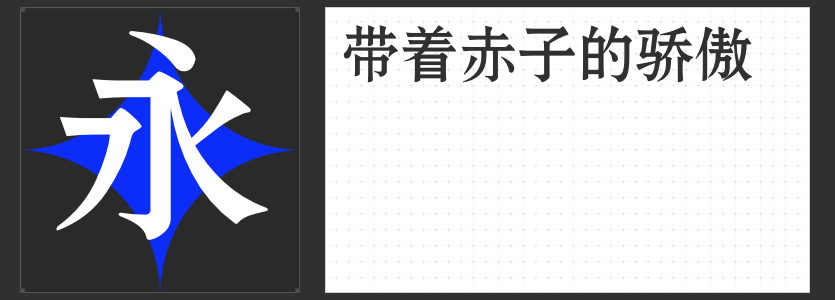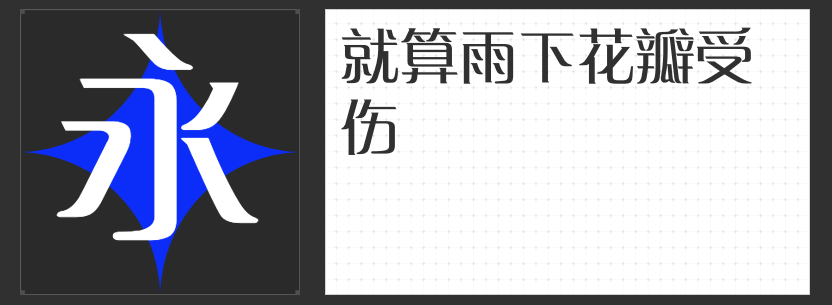
广告就是要端庄大气!四款字体推荐
在广告设计中,字体选择至关重要,它不仅能够传达信息,还能强化品牌形象,激发观众情感。今天,为大家推荐四款来自励字字库的精选字体,它们各具特色,非常适合用于广告设计中,为你的创意增添无限可能。
第一款推荐的是励字超级勇士简 中粗。这款字体以其严谨庄重的字型设计脱颖而出,笔画以直线为主,弧线简洁明了,展现出一种力量与美感并存的视觉效果。起笔与收笔采用斜切手法,与转折处的圆弧处理相得益彰,使得整体字体流畅而舒适,非常适合用于需要强调力量感和专业度的广告中。
接下来是励字励倩简。这款字体基于扁平硬笔的书写轨迹设计,笔锋柔和,避免了尖锐感,以微小的圆弧呈现,给人一种温婉而舒畅的感觉。字型方正饱满,笔划粗细对比适中,既婉转妩媚又不失温顺乖巧,适用于营造温馨、亲切的广告氛围。
励字宋黑简则是一款融合了黑体与宋体特点的字体。它保持了黑体的端正大方,横竖笔画挺拔有力,同时融入了宋体的典雅与工整。字体清秀,横轻竖重,结构均匀,笔法严谨,既美观又实用,非常适合用于需要展现品牌专业形象与高端品质的广告设计中。
最后推荐的是励字粗圆简繁。这款圆体字体字形端正严谨,笔画四周圆润,给人一种和谐而亲切的感觉。在广告设计中使用这款字体,能够营造出一种温馨、友好的氛围,特别适合于儿童产品、家居用品等温馨主题的广告宣传。
这四款励字字库字体各具特色,能够满足不同广告场景的需求。无论是强调力量感、温馨亲切还是专业高端,都能在这些字体中找到合适的选择。让你的广告设计更加出彩,吸引更多目光!